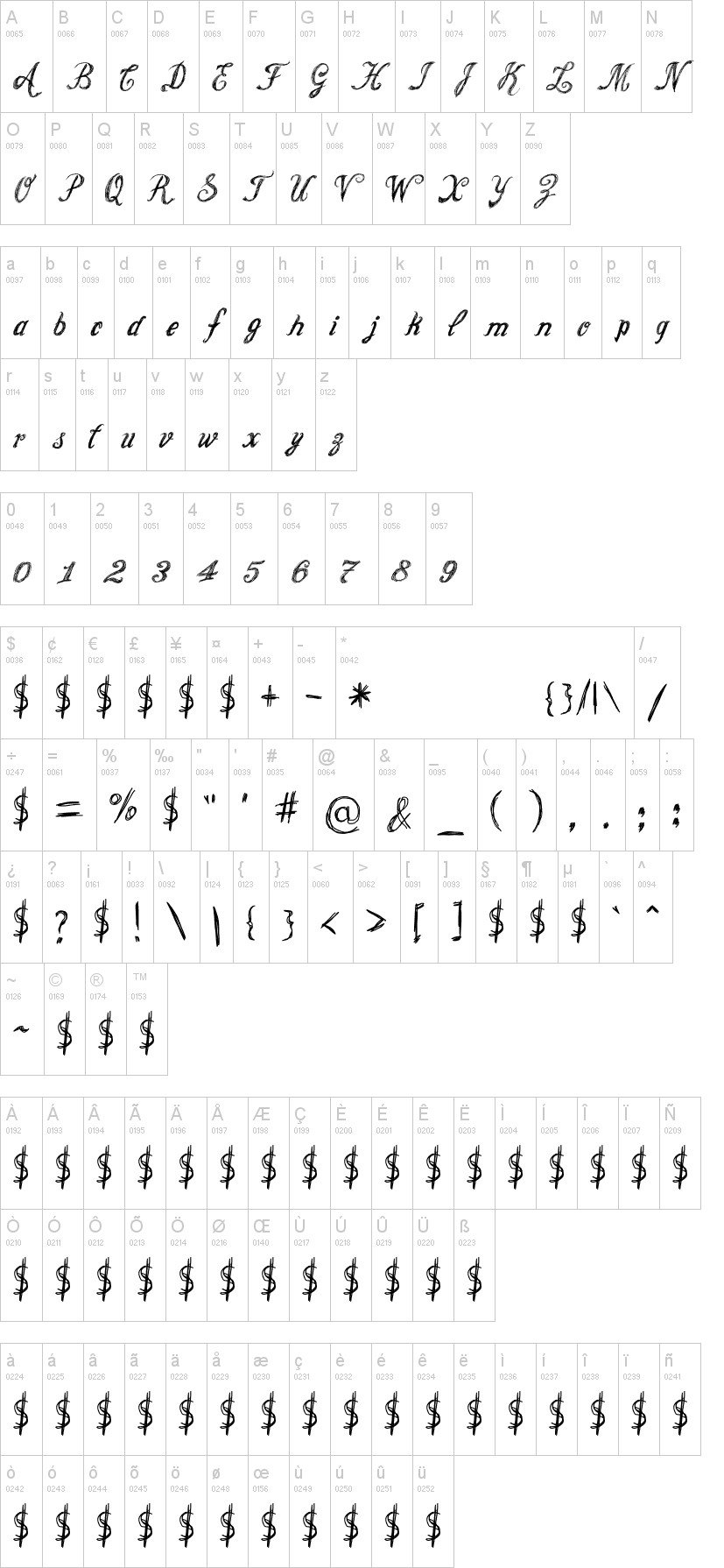
Cursive Option 字体是一款细腻优雅的手写体字体,它是由一位日本设计师 Mika Melvas 创作的,它结合了手写体和草书体的特点,具有更具有自然和柔和的感觉,可以用于商业和个人设计。它的笔画宽度比较细,可以带来更加细腻的感觉,可以用于创作卡片、海报、标志等设计作品。内容介绍
Cursive Option是一款非常不错的手写艺术字体,具有很好的视觉感,适合于文化类的宣传设计、商业类品牌的广告和产品包装设计以及个性化文字排版等较多场景。